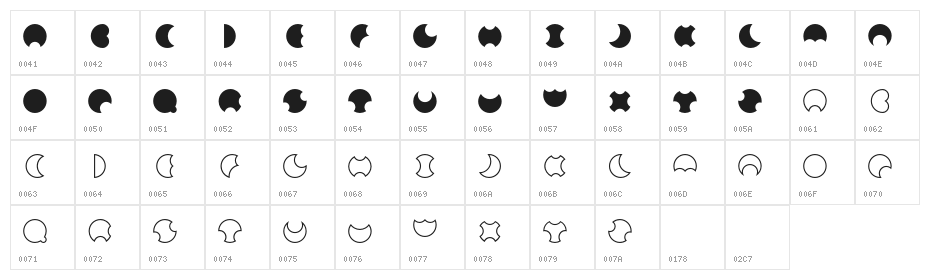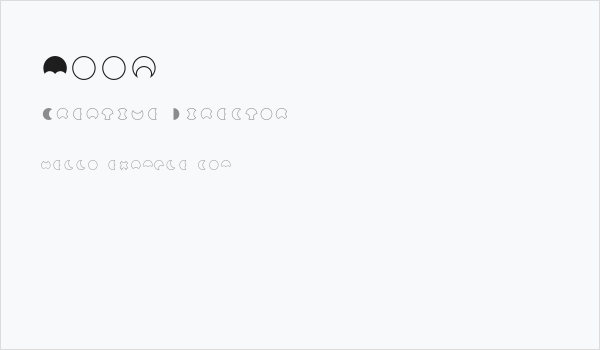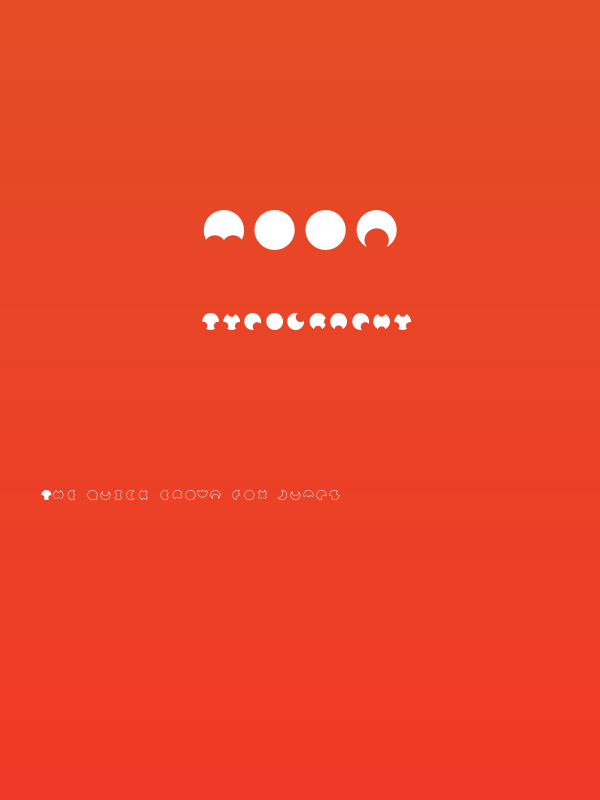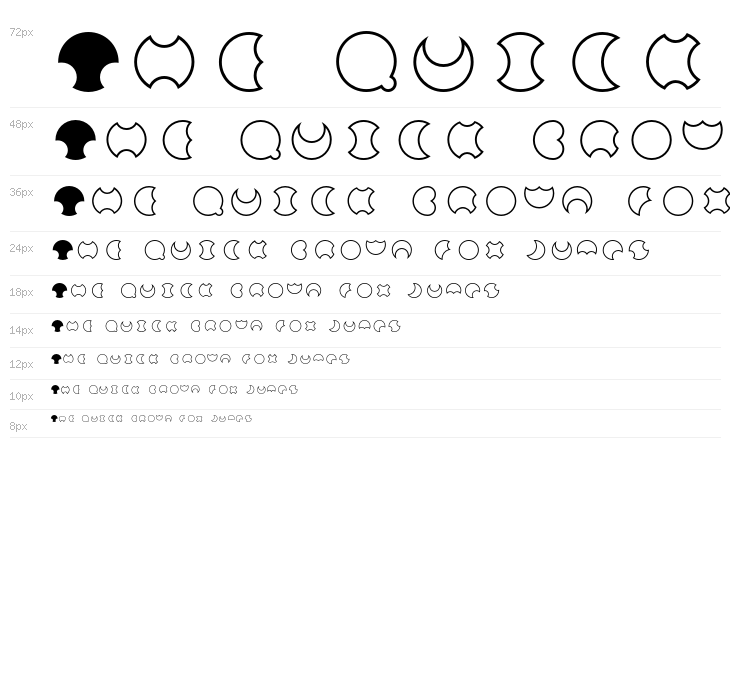
Moon Font
此字体包含 56 个字符。点击任意字符查看详情。
| 使用场景 | Logos, Decorative elements |
| 推荐项目 | Ideal for use in branding, packaging, or as decorative elements in digital and print media. It could also be used in fashion design or interior decor to add a modern, celestial touch. |